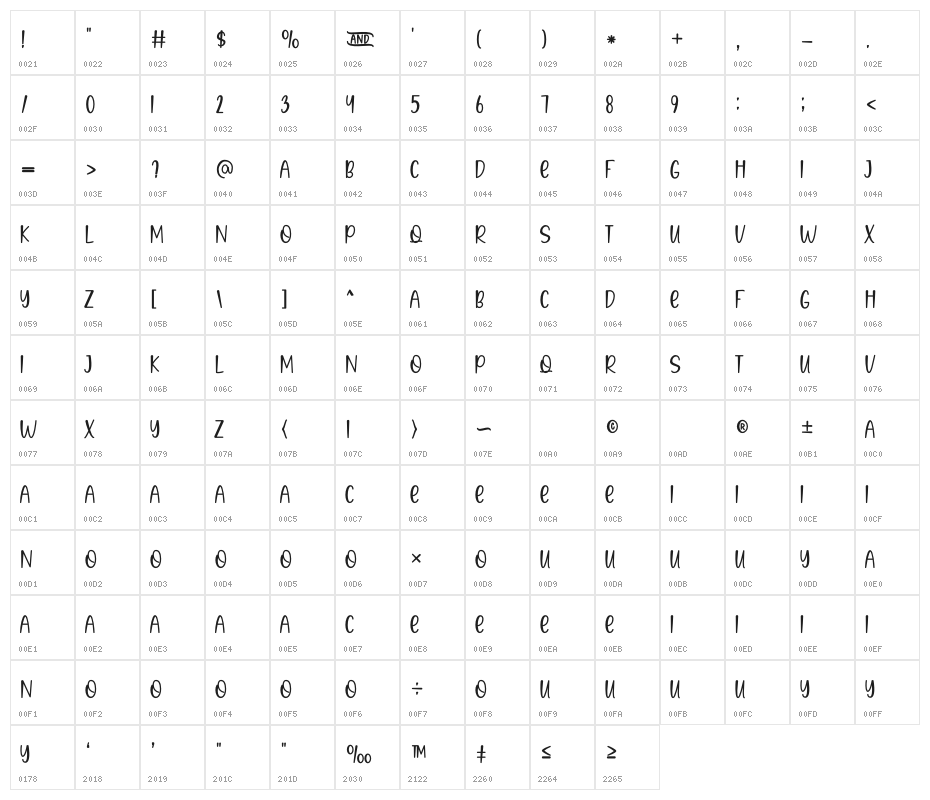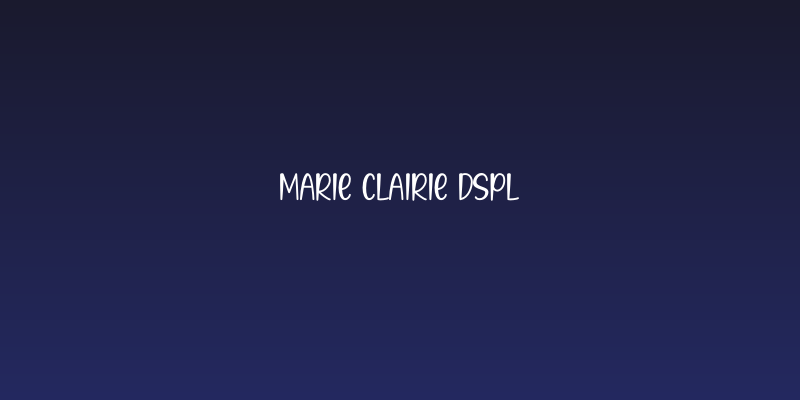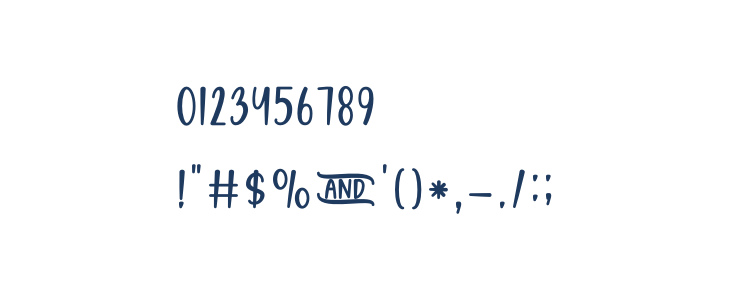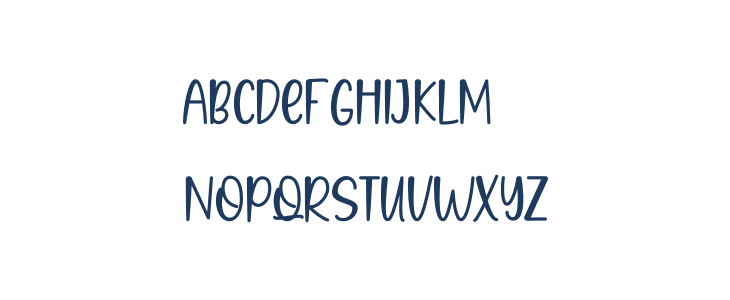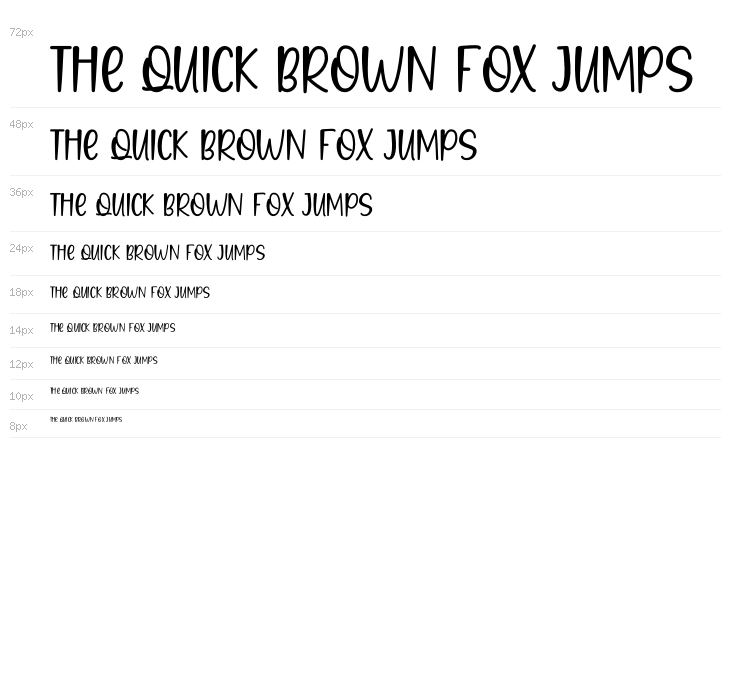
Marie Clairie Dspl Font
| Gesamtstil | Playful, Casual, Handwritten |
| Anwendungsfall | Headlines, Logos, Posters, Informal text |
| Vorgeschlagene Projekte | Greeting cards, children's books, informal branding, social media graphics, posters. |